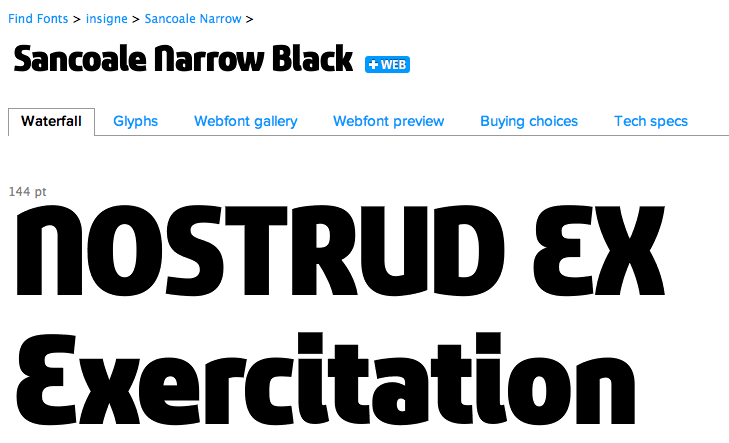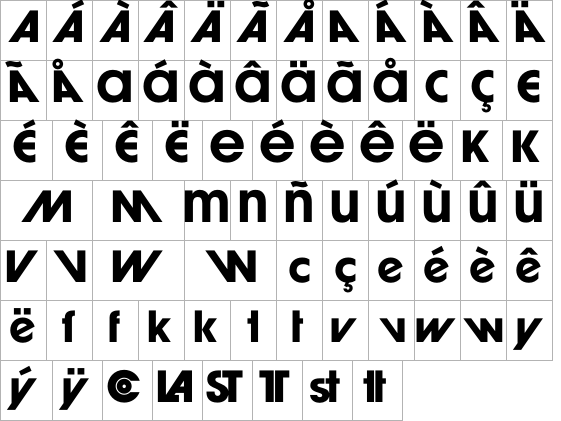
Schrift mit rundem Versal-E?
Ich suche derzeit eine serifenlose Schrift, bei der das Versal-E in runder Form – wie eine gespiegelte 3 – enthalten ist. Bei meiner Suche bin ich auf die Locator Display und die Grover gestoßen, allerdings sind diese mir etwas zu technoid. Schriften, wie die Pump, lasse ich mal außen vor.
Dank dir für den Hinweis, aber bei der Suche findet man allenfalls Schriften, die man getrost in die Kategorie unbrauchbar packen kann. :-(
Ich fürchte, dass diese sehr spezielle Form des E immer mit sehr "speziellen", als charismatischen, sonderbaren, exzentrischen Schriftentwürfen einhergeht, da so eine E-Form meist als Fremdkörper in einem sonst neutralen Schriftentwurf wahrgenommen werden würde, was nicht wirklich Sinn der Sache ist.
Am ehesten wirst du vermutlich noch bei Swash-Kursiven fündig werden, also bei am Geschriebenen orientierten Schriftarten. Meine noch nicht fertige Canapé hat diese E-Form z.B. in der Swash-Alternative der Kursiven eingebaut – dort aber unterstützt mit entsprechenden Formen bei vielen anderen Buchstaben.
Z.b. die Auto Italic 3 hat diese E-Form.
Wie du siehst, sind da aber auch alle anderen Buchstaben entsprechend schwungvoll ausgeführt ...
Auch die "Sauna Italic Swash" aus dem selben Haus hat dieses E.
Ich fürchte, dass diese sehr spezielle Form des E immer mit sehr "speziellen", als charismatischen, sonderbaren, exzentrischen Schriftentwürfen einhergeht, da so eine E-Form meist als Fremdkörper in einem sonst neutralen Schriftentwurf wahrgenommen werden würde, was nicht wirklich Sinn der Sache ist.
Das dachte ich mir. Nichtsdestotrotz hoffe ich, dass sich vielleicht doch noch die eine oder andere Groteskschrift finden lässt, in der so ein gesuchtes E zumindest als Alternativbuchstabe hinterlegt ist. Gerade bei Headlineschriften ist ja das Abweichen von der typischen E-Form durchaus zulässig. Beispielsweise verfügt die Gloriola über ein Alternativ-E, das dem gesuchten recht nahe kommt.
Darf man fragen, warum Du eine Schrift mit entsprechendem E suchst? Vielleicht könnte man dann zielgerichteter antworten.
Ich stehe ganz am Anfang einer kleinen Corporate-Design-Entwicklung. Für die Wortmarkengestaltung habe ich erste fixe Ideen, die ich anhand einzelner Schriften durchspiele. Dazu gehört auch ein Ansatz mit dem runden E, das die Form der Bögen eines Bs aufgreifen soll. Sollte sich daraus was konkreteres ergeben, werde ich den Buchstaben wahrscheinlich selber zeichnen. Für die Ideenfindung reicht aber erst einmal eine existierende Schrift.
Vielen Dank für die vielen Vorschläge. Die Tarzana Wide entspricht in etwa der Richtung, die ich verfolge.